「打」のきれいな書き方を解説します。
「打」の見本
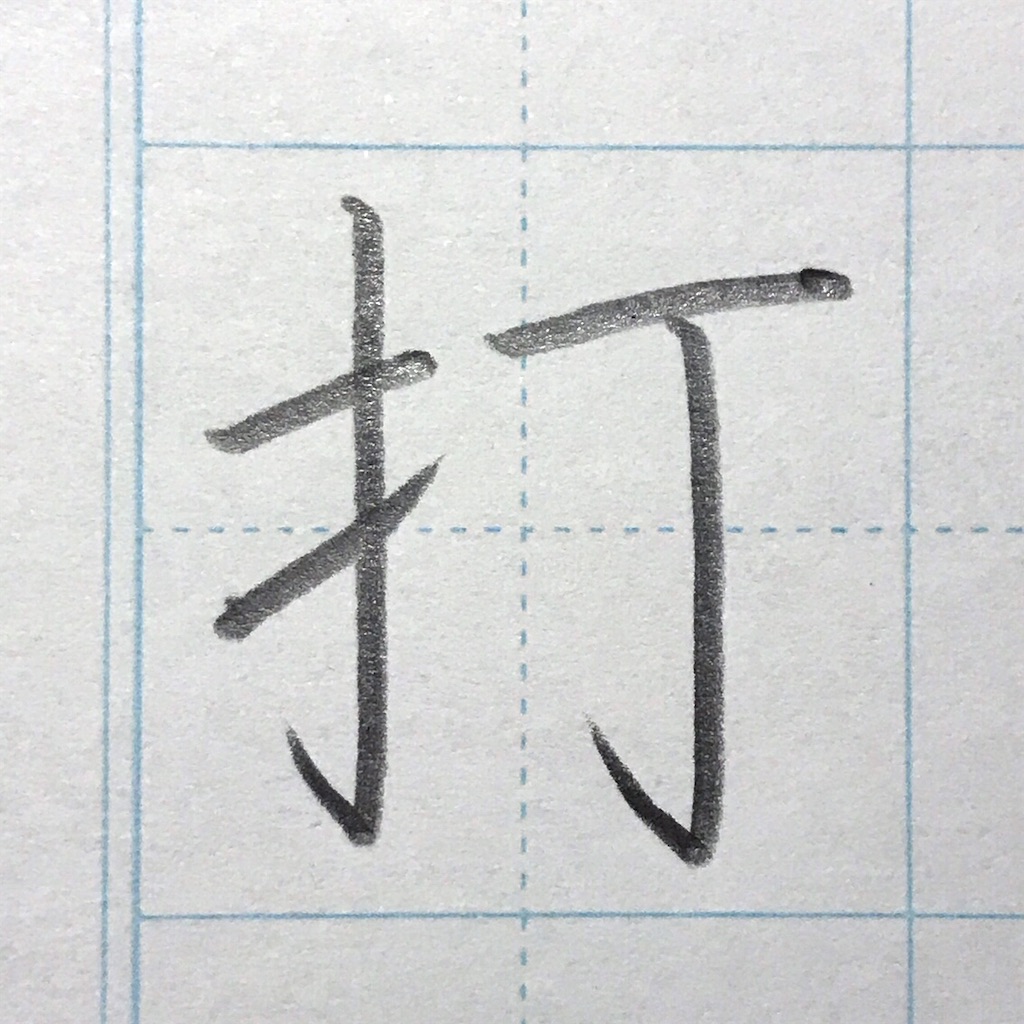
「打」の書き順
5画です。
書き方解説
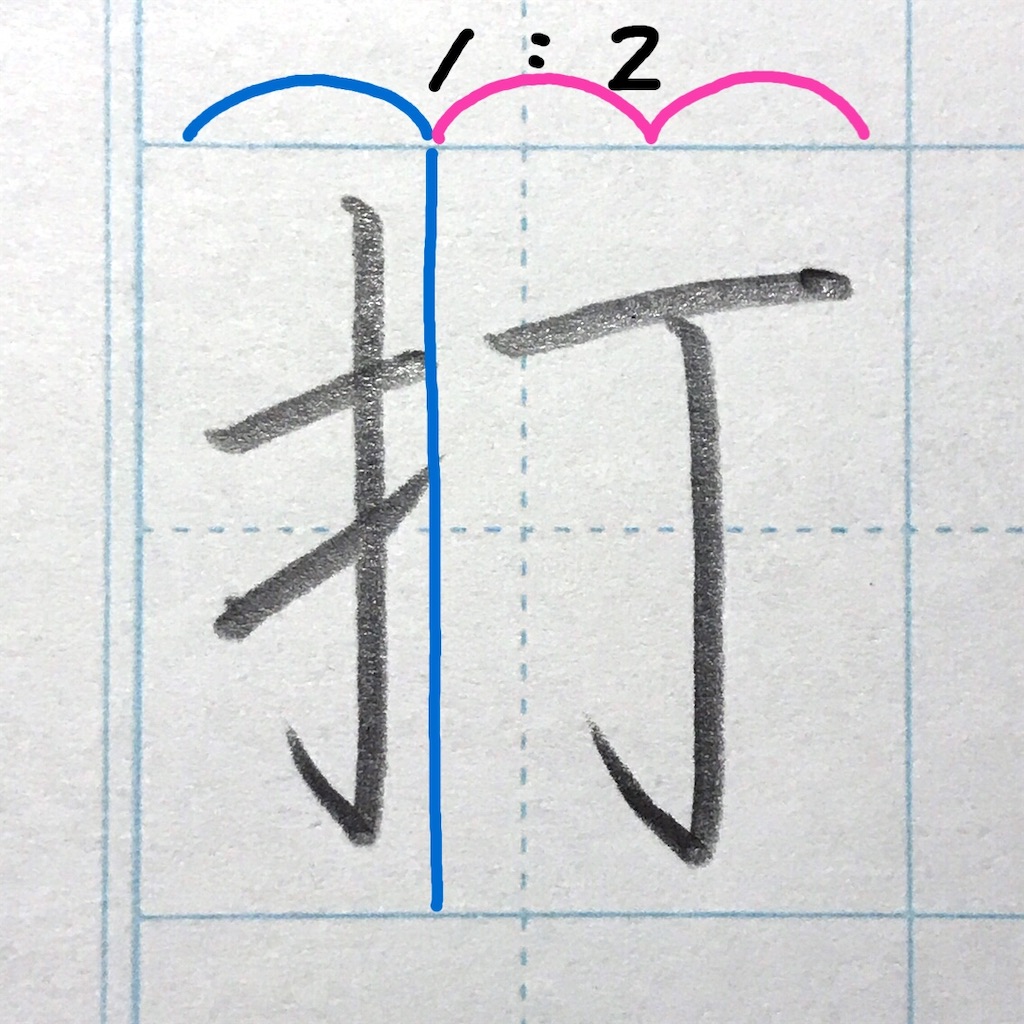
全体構成は、「てへん」1 対「つくり」2 を目安に。
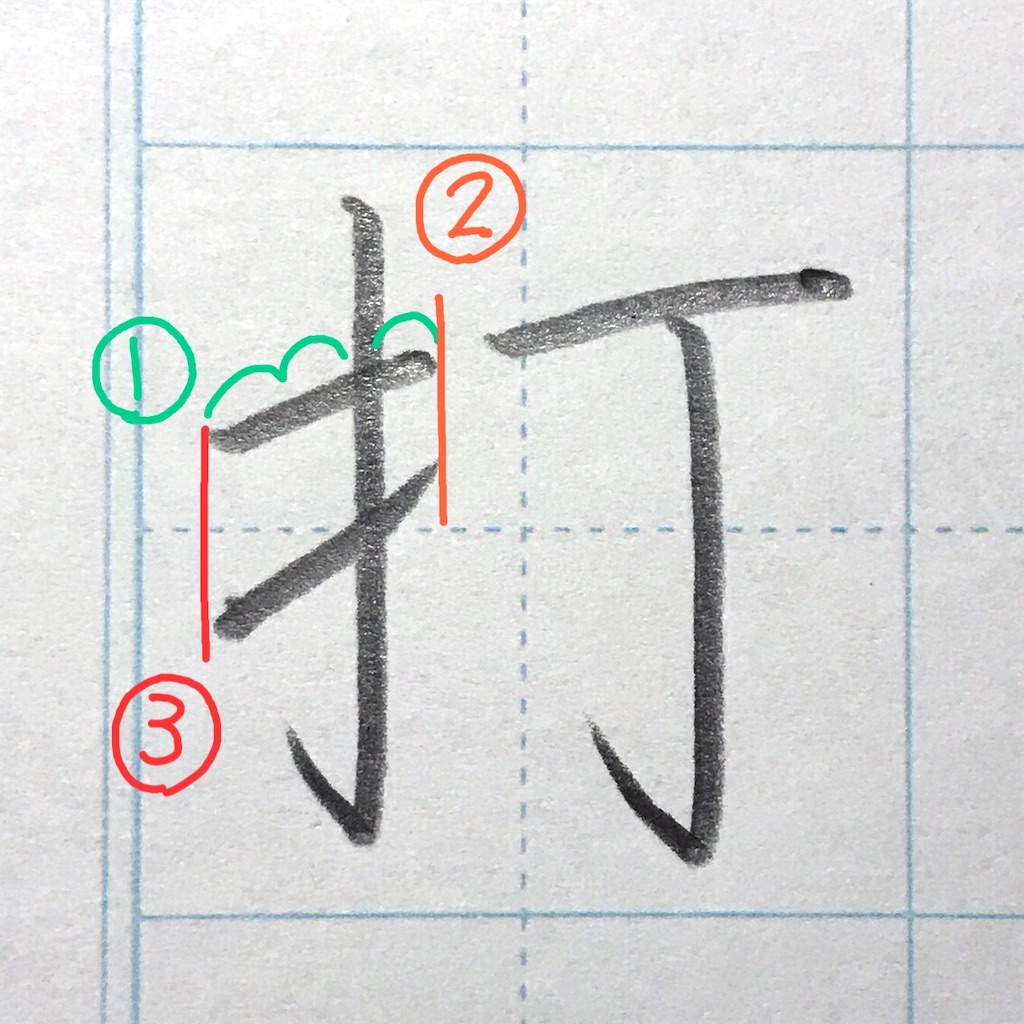
①2対1
②揃える。(つくりのジャマをしないように。)
③左端も揃えるとスッキリします。
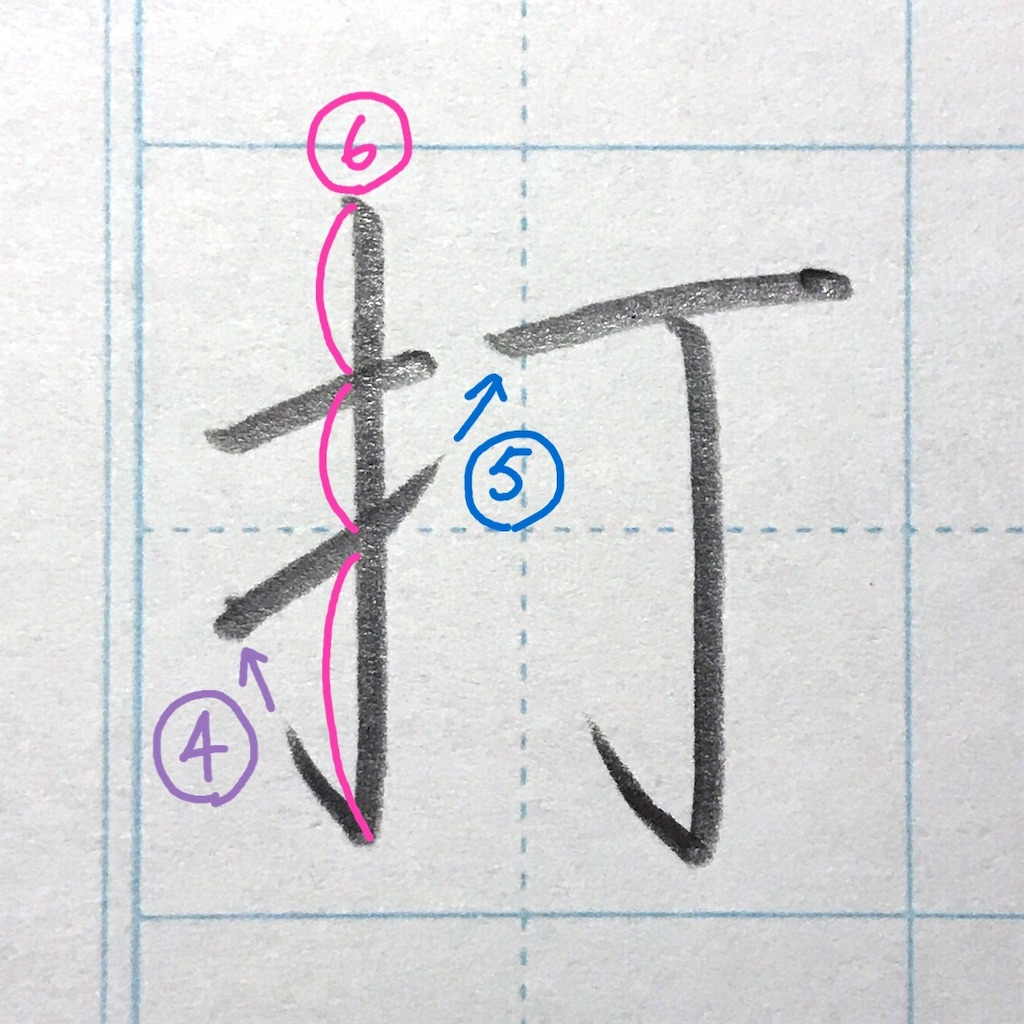
④ハネは次の画に向かいます。
⑤3画目の「シュっ」も次の画に向かうと◎。
⑥「てへん」の縦画と横画のバランス。
1対1対2 くらいがベスト。
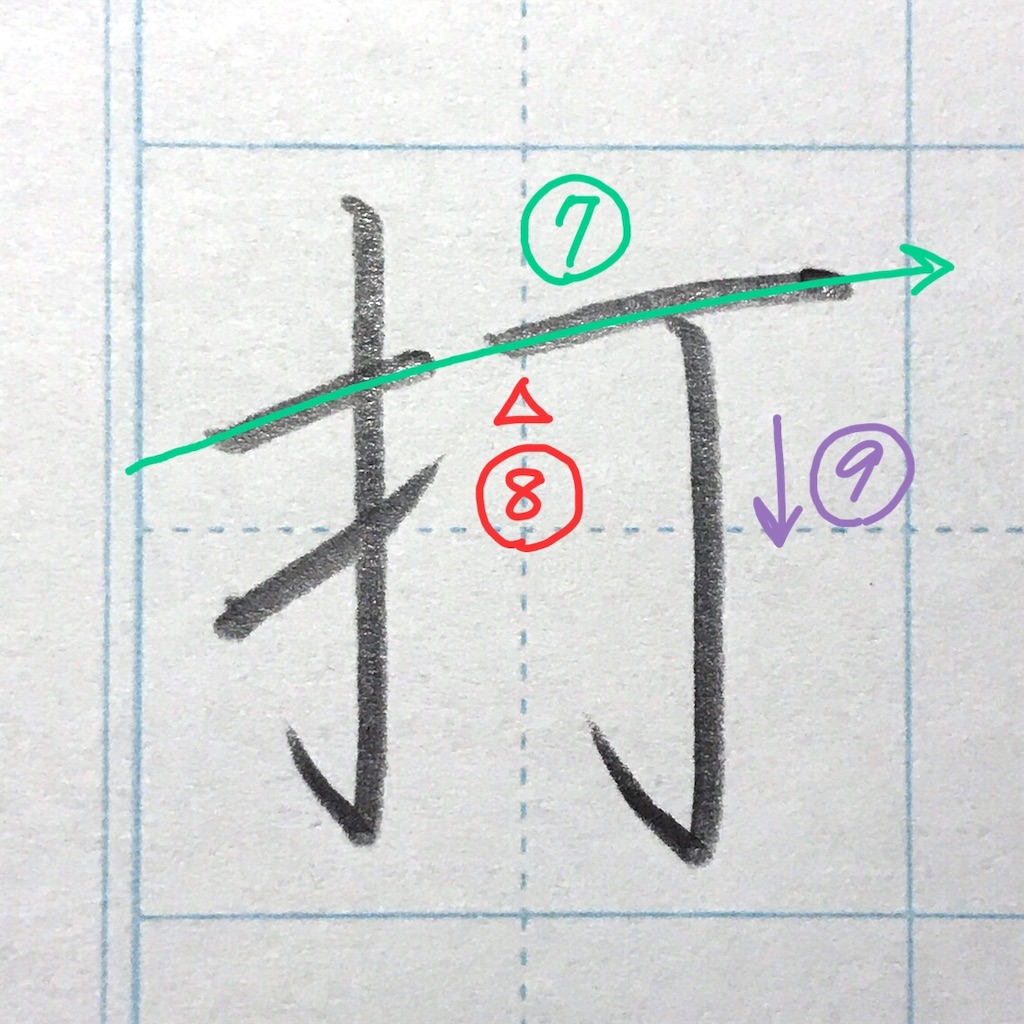
⑦1画目と4画目は横に並んで、右上がりに揃うと◎。
⑧4画目のはじまりは、ほぼ中心から。
⑨5画目、まっすぐ下ろします。
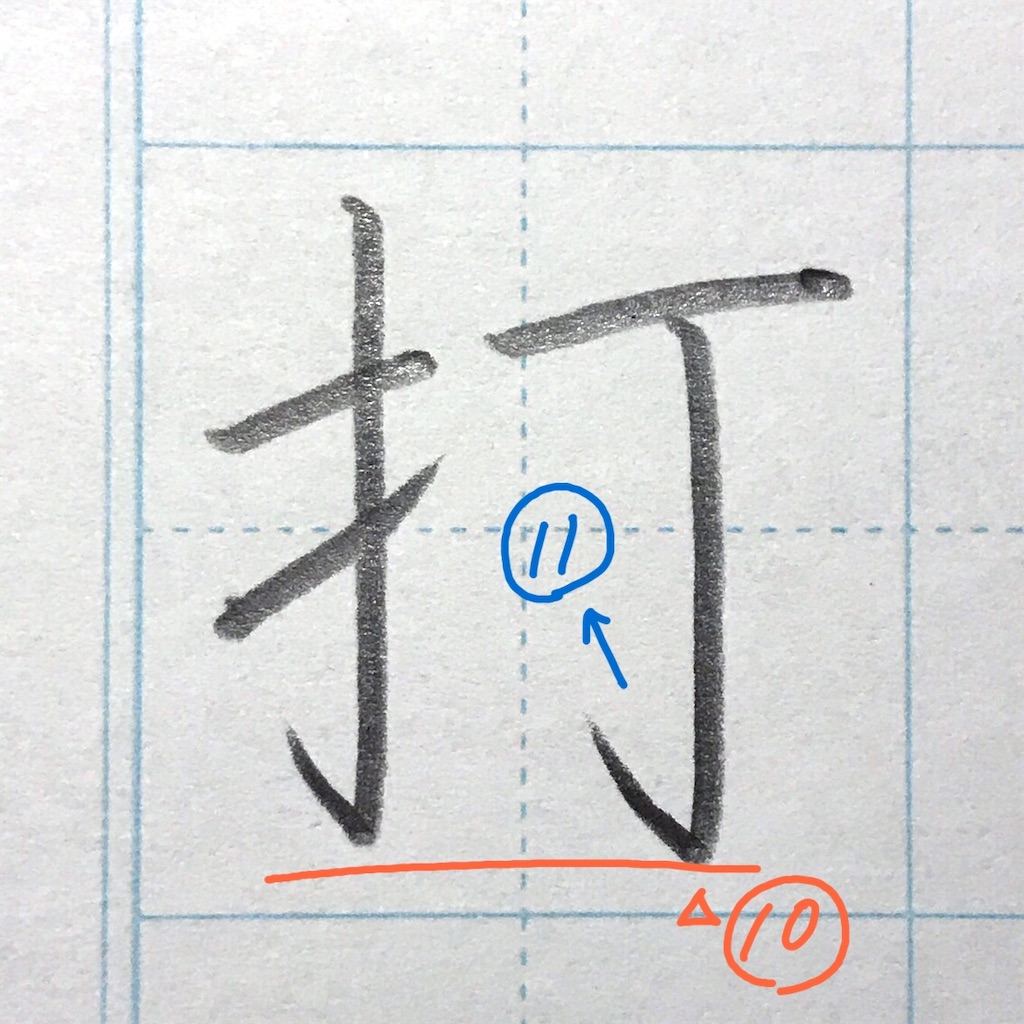
⑩「丁」の終わりが少しだけ下になるように。
⑪最後のハネは大きくのびのびと。
完成!